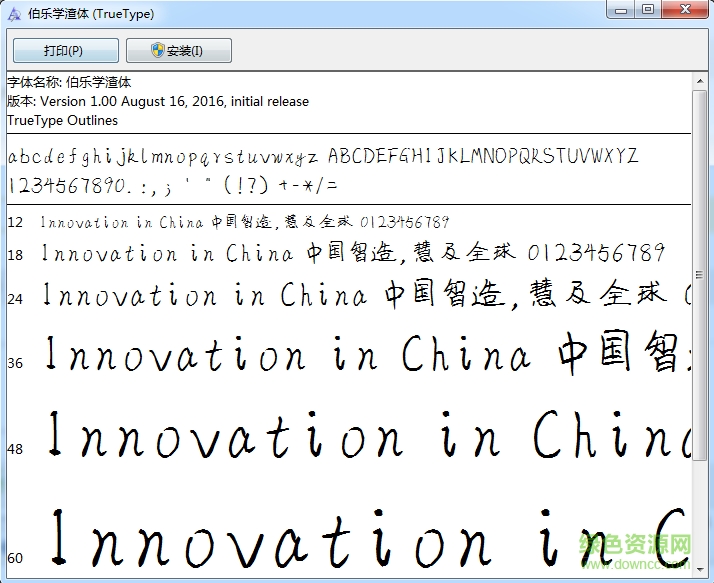
伯乐学渣体是一款典型的手写体字体,看似不规则的笔画但有着自己的独特,感受学渣的韧性和不言弃的坚持,喜欢的普就来绿色资源网尝试吧!
伯乐学渣体作为一款拨了字体,同是手写风格,字体完整支持中英文书写,有着合适的宽度和高度,常用于平面设计、名片设计、海报设计、排版印刷等行业,有着不错的观赏体验。
伯乐学渣体 Version 1.00 August 16, 2016, initial release字体(字体家族名称:伯乐学渣体;字体风格样式名称:伯乐学渣体),共有6917个字符。